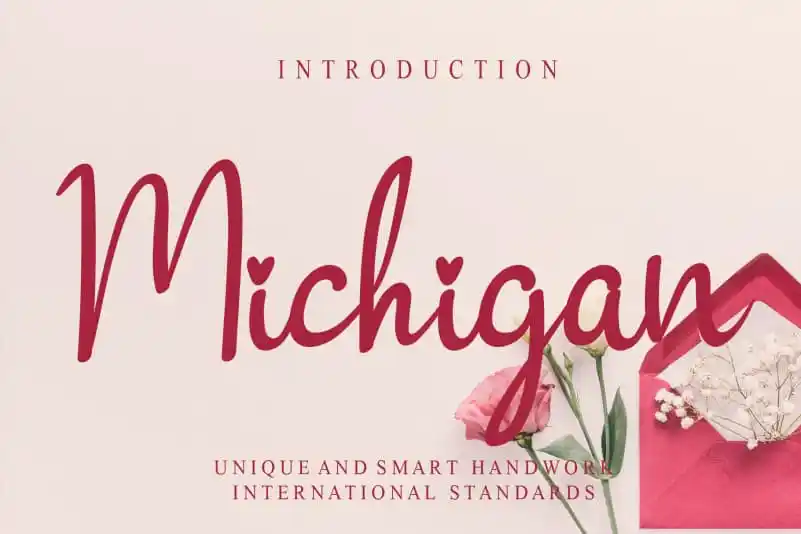
Esta Michigan Script Font é uma elegante escolha para quem busca uma escrita cuidadosamente elaborada e encantadora que transmite sensibilidade e delicadeza. Com a influência do traço humano, essa fonte oferece um estilo autêntico que se assemelha à escrita de alguém escrevendo livremente em uma folha de papel, sem segredos ou restrições. Seja para criar cartões de aniversário personalizados ou trabalhos de arte gráficos com alma, essa fonte Michigan Script proporcionará aos designers um toque criativo e único que se torna o destaque do seu projeto. Ela é perfeita para aqueles que buscam uma fonte que expressa a essência da arte em movimento, trazendo vida e personalidade à sua produção visual. Com uma paleta de traços suaves e fluidos, essa fonte oferece os detalhes finos necessários para criar textos memoráveis, fazendo dela um complemento perfeito tanto para o trabalho comercial quanto pessoal.